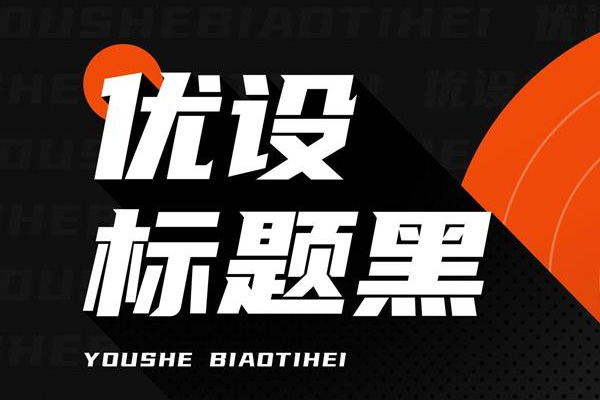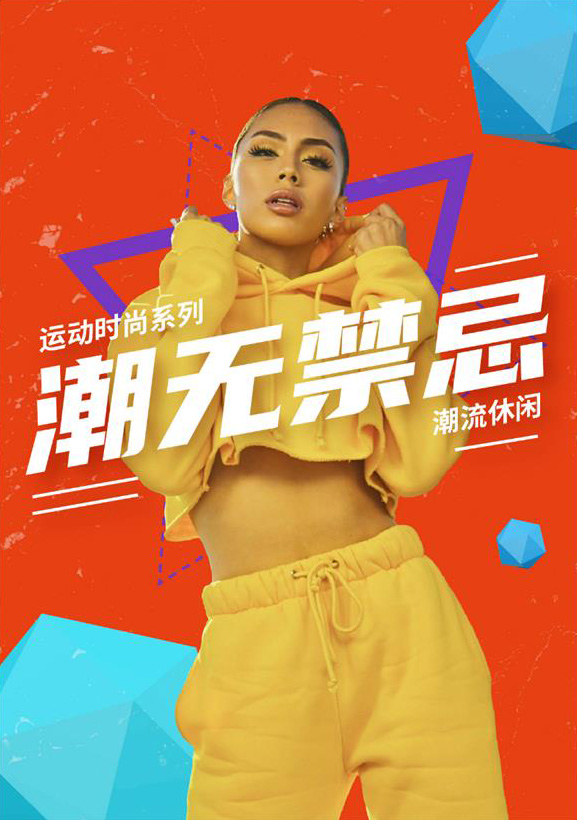
优设标题黑
「优设标题黑」是一款具有通用性和速度力量感的精美艺术标题字体。基于黑体字形打造,整体字形稳重适度,同时采取大字面和粗壮的笔画设计,将力量感体现得淋漓尽致。每个字符以8°的角度倾斜,使得字体焕发出强烈的速度感。为了保持字体的稳定性,设计师对整体字身进行了宽扁设定。此外,起笔和弯钩部分的独特尖角设计不仅凸显了几何感,也方便后期调整。这款字体在各类品牌广告和产品包装设计的标题中具有很高的适用性!
优设标题黑效果预览
优设标题黑字体效果预览